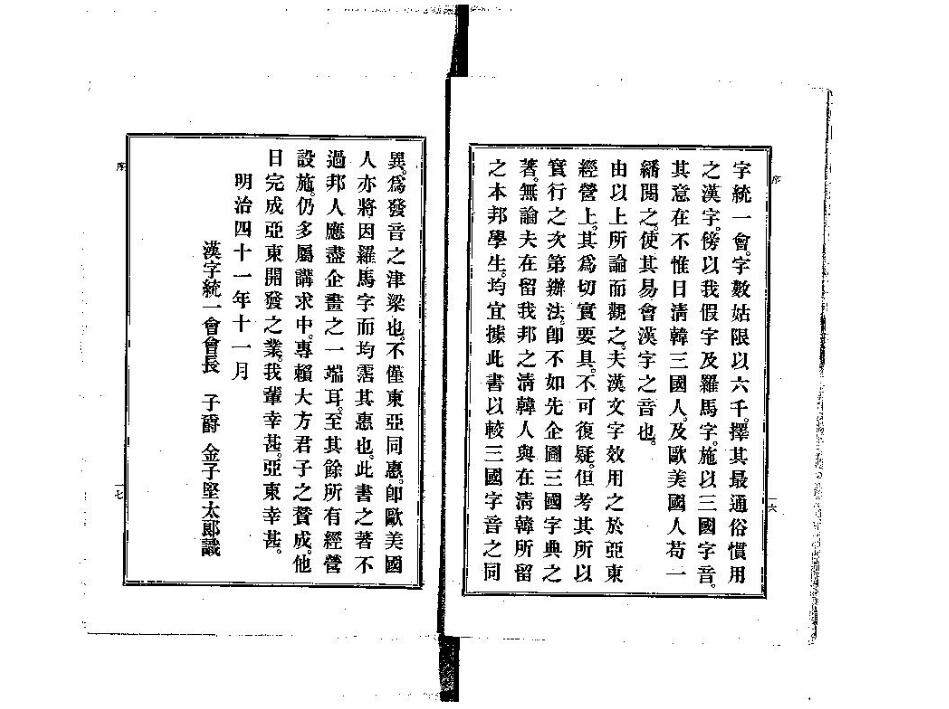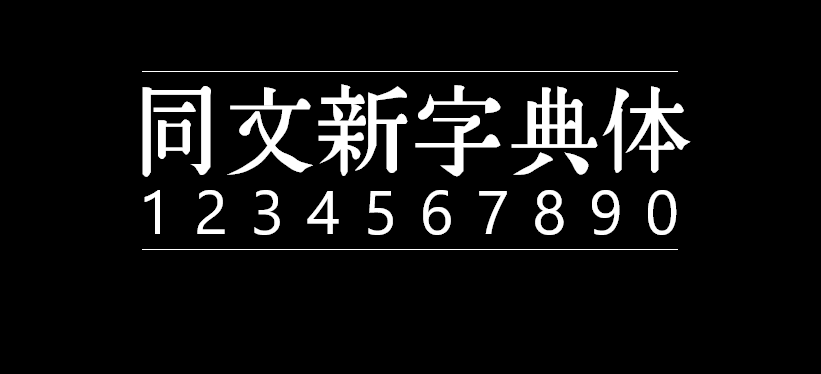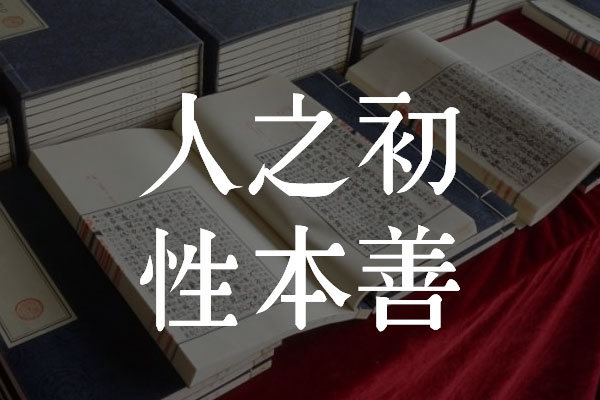
同文新字典体
同文新字典体(出島明朝フォント dejima-tsu3)的作者是日本的Yoshiki Hayashi,他在Github上建立了这款字体的开源项目,同文新字典体是从日本古籍《同文新字典》和《 [東京築地活版製造所]活版見本 》复刻而成的一款字体。
因为同文新字典体是一款从古籍复刻而来的字体,所以该字体主要以繁体字为主,也包括部分简体字。